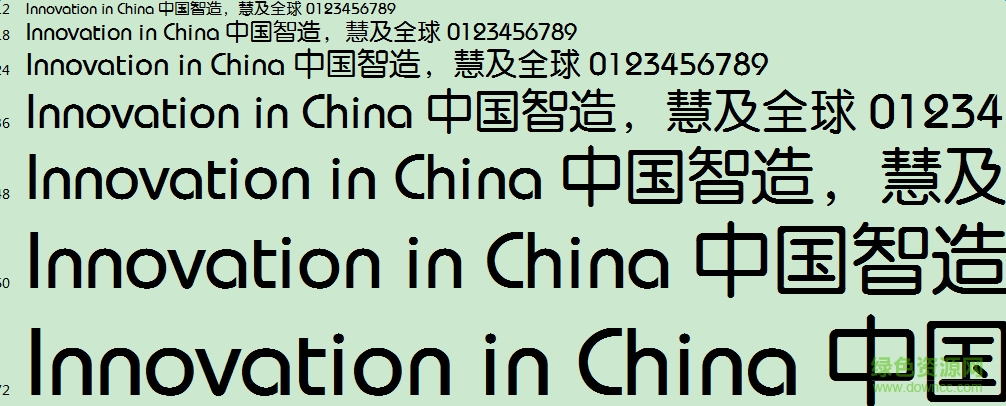
default.ttf字體是一款非常有特色的英文字體,非常適用于文字排版、海報(bào)廣告設(shè)計(jì)、藝術(shù)設(shè)計(jì)等方面,有需要的朋友不要錯(cuò)過(guò)了,歡迎大家來(lái)綠色資源網(wǎng)免費(fèi)下載使用!
這款字體剛?cè)岵?jì),透著文化氣息,它不光具有優(yōu)秀的機(jī)能性,還具備了書(shū)寫(xiě)上運(yùn)筆的視覺(jué)性。既規(guī)范、均一,又端莊、秀美、靈動(dòng)。